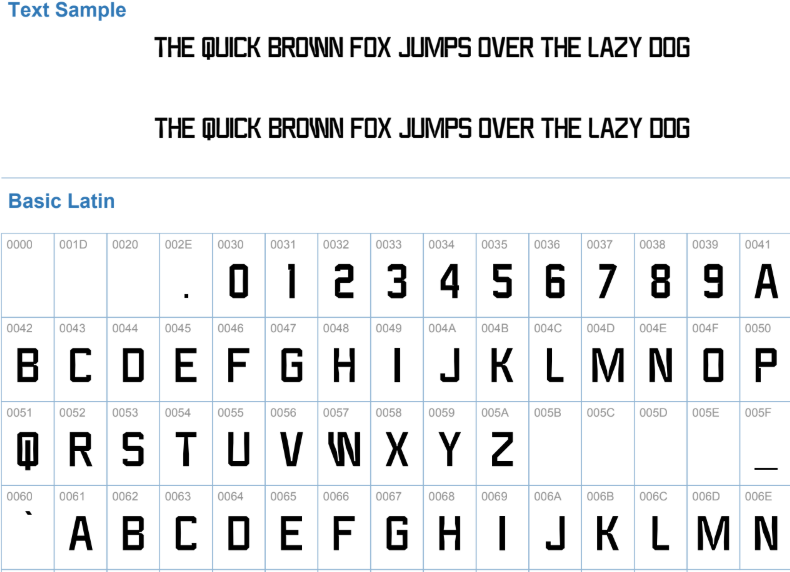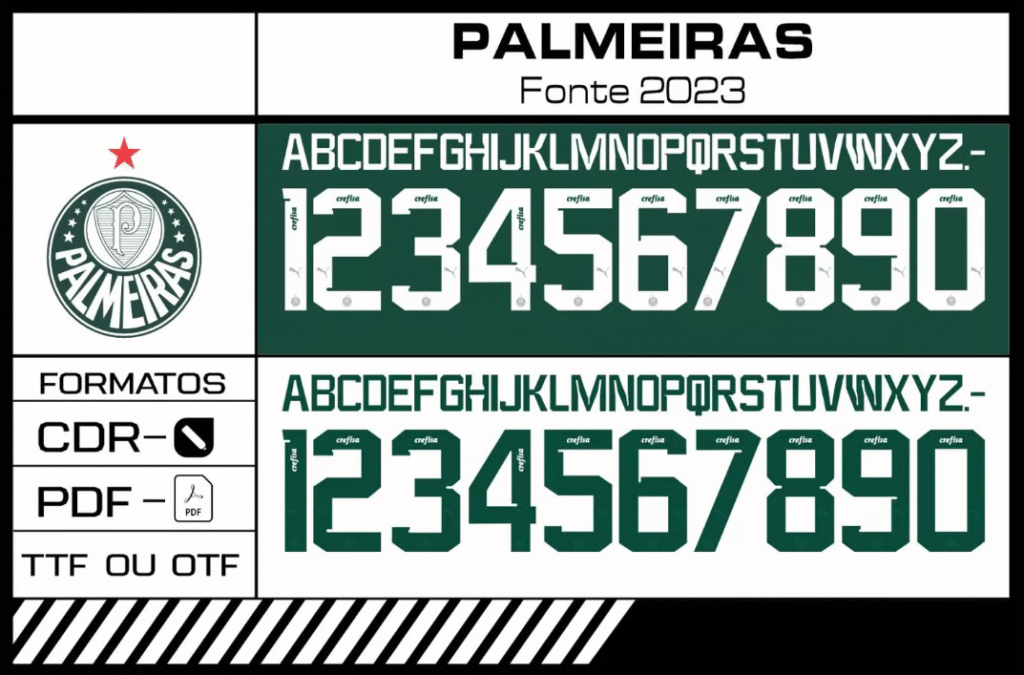
A identidade de um time campeão se vê nos detalhes. Em 2023, a Puma acertou em cheio no design dos uniformes da Sociedade Esportiva Palmeiras, e a tipografia usada nas costas dos jogadores é parte fundamental dessa estética.
Mais do que apenas números e letras, essa fonte carrega o peso da história recente e a energia da torcida que canta e vibra. Dos gramados do Allianz Parque diretamente para o seu computador, trazemos a cobiçada fonte Palmeiras 2023 para elevar o nível dos seus projetos de design.
Estilo e Design
O estilo da fonte Palmeiras 2023, desenvolvida pela Puma, é uma clara mistura de modernidade e força. Ela abandona traços excessivamente arredondados e aposta em cortes mais definidos, com ângulos retos e uma leve inclinação que sugere movimento e dinamismo.
É uma tipografia limpa, mas muito robusta. A legibilidade é excelente, garantindo que nomes e números sejam vistos claramente à distância durante as transmissões. Usada nos uniformes principal (verde) e reserva (branco) da temporada, essa fonte se tornou sinônimo da performance técnica e da seriedade do “Verdão” em campo.